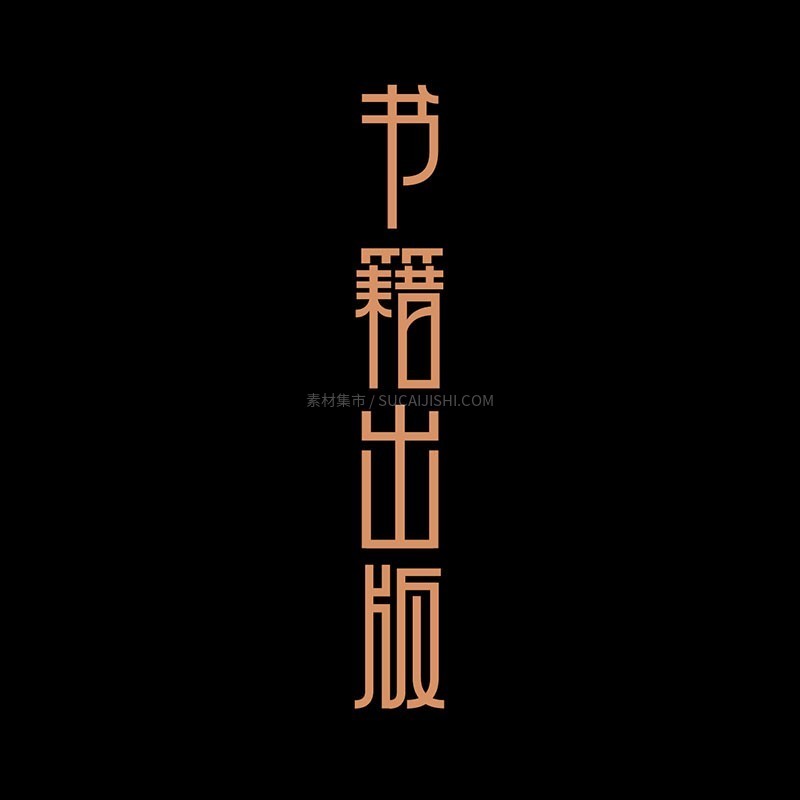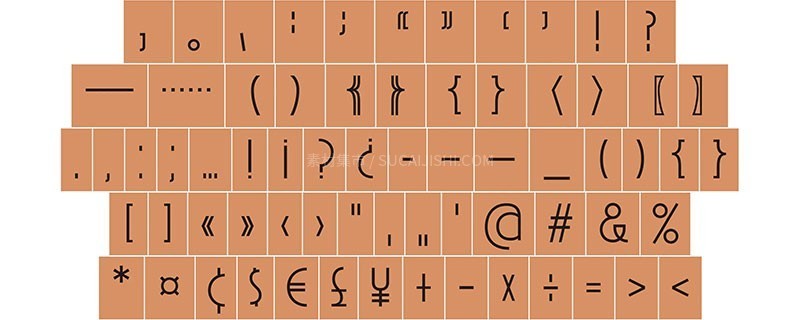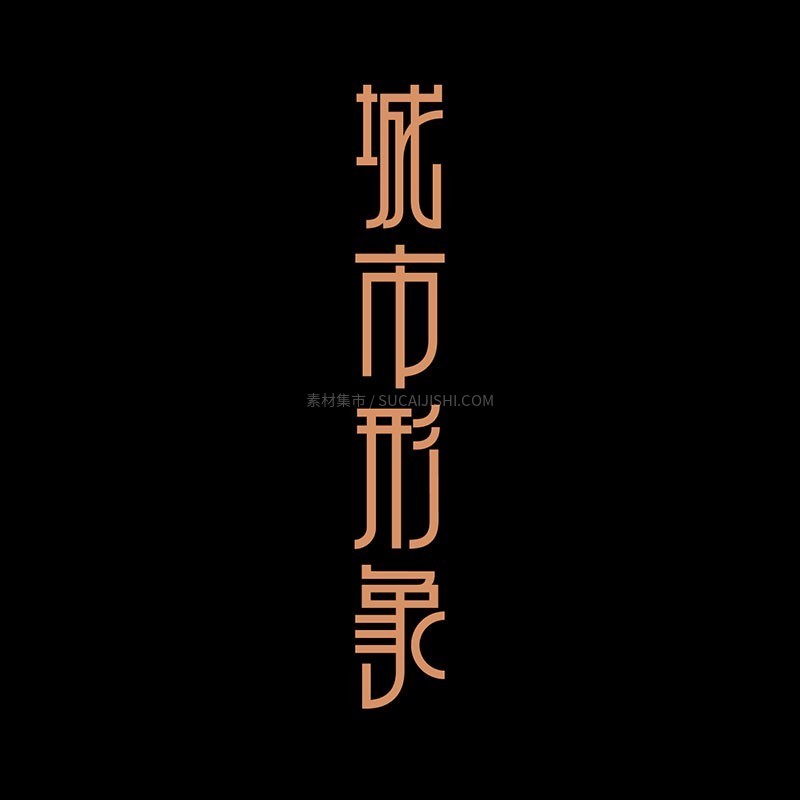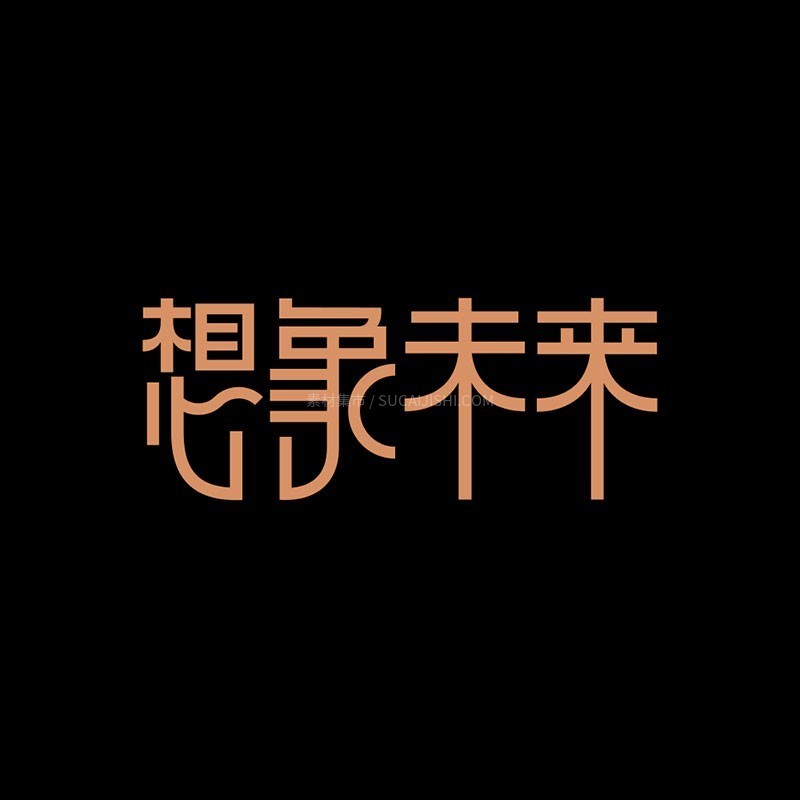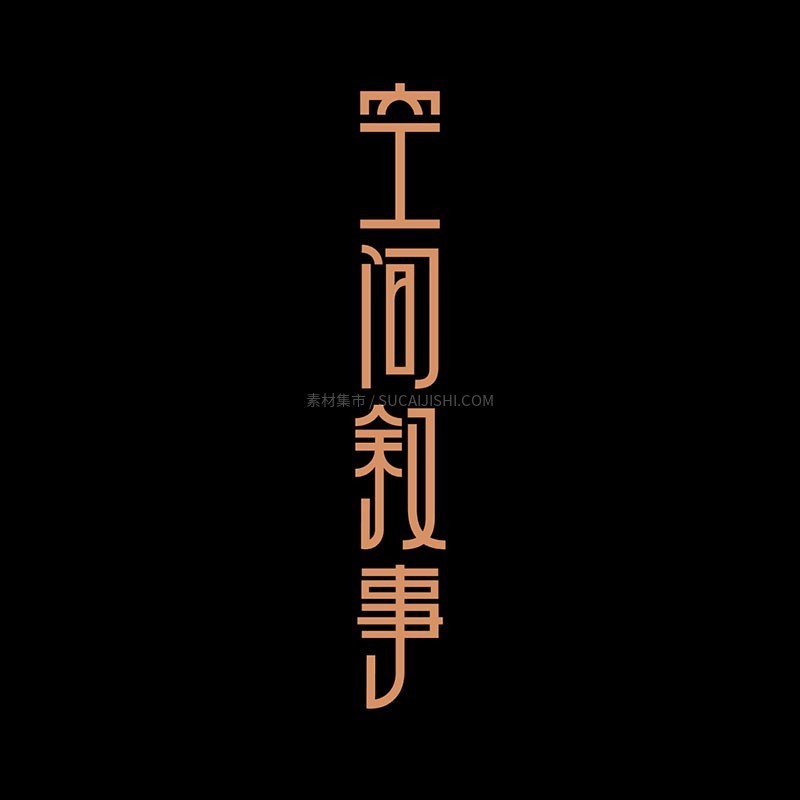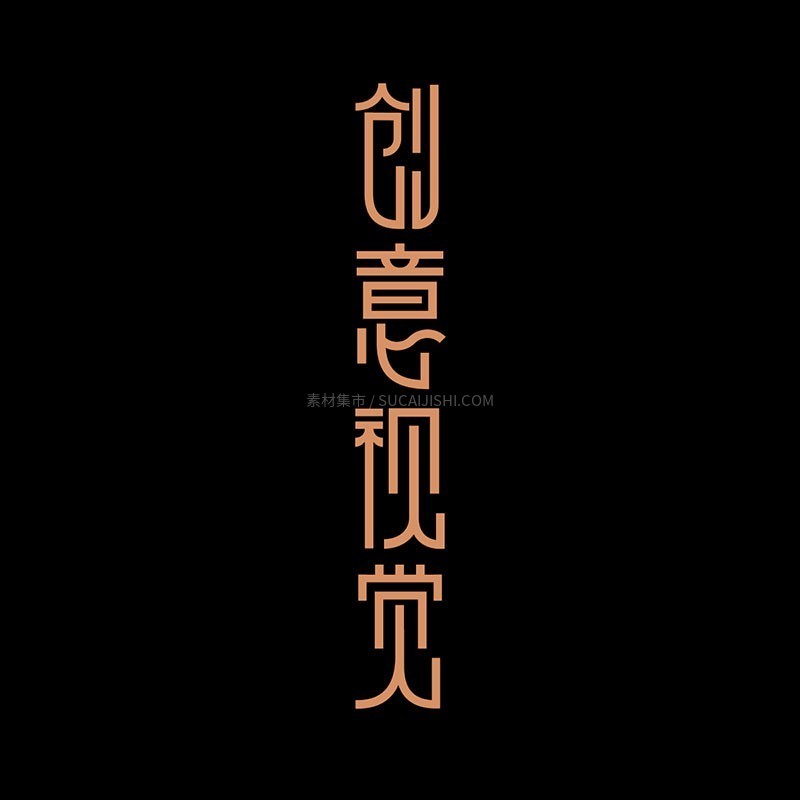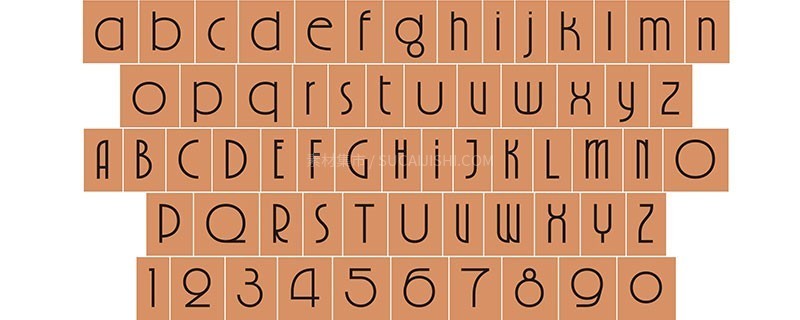
上海摩登体(Shanghai Modeng)是中国首个以城市文化为源流的中西文字库,它溯源于 1930至40年代 上海都市文化涌现的装饰艺术(Art Déco)运动,旨在传承其融合多元与创新未来的时代精神。这款字体以现代字库技术为基底,突破传统汉字结构,将装饰艺术的几何美学精髓注入骨骼。其字形笔画由直线与圆弧精密组合而成,粗细均衡、刚柔相济;架构采用字面高耸的设计,如建筑般挺拔有力,在几何秩序中迸发出向上的动感。西文字体、阿拉伯数字与标点符号同样遵循统一的设计逻辑,其中西文小写字母采用较高的x高度并强调圆弧造型,数字富有弹性和趣味,共同塑造出先锋、摩登且充满想象力的独特视觉语言。